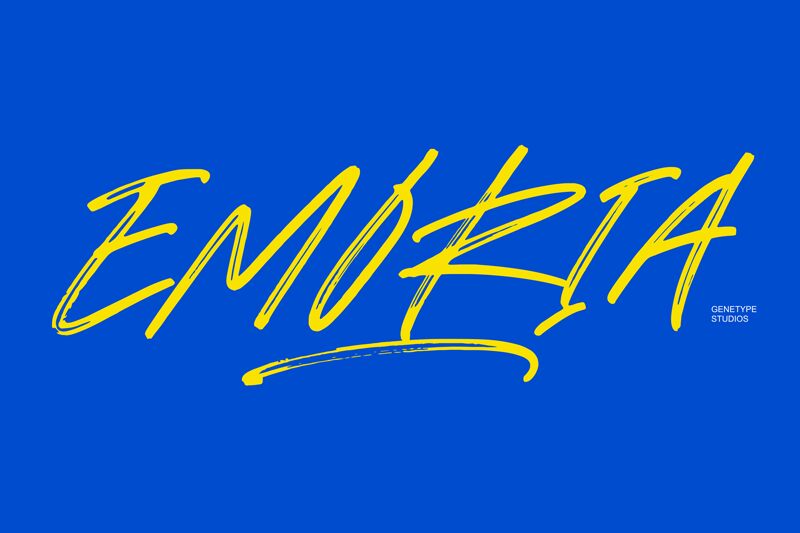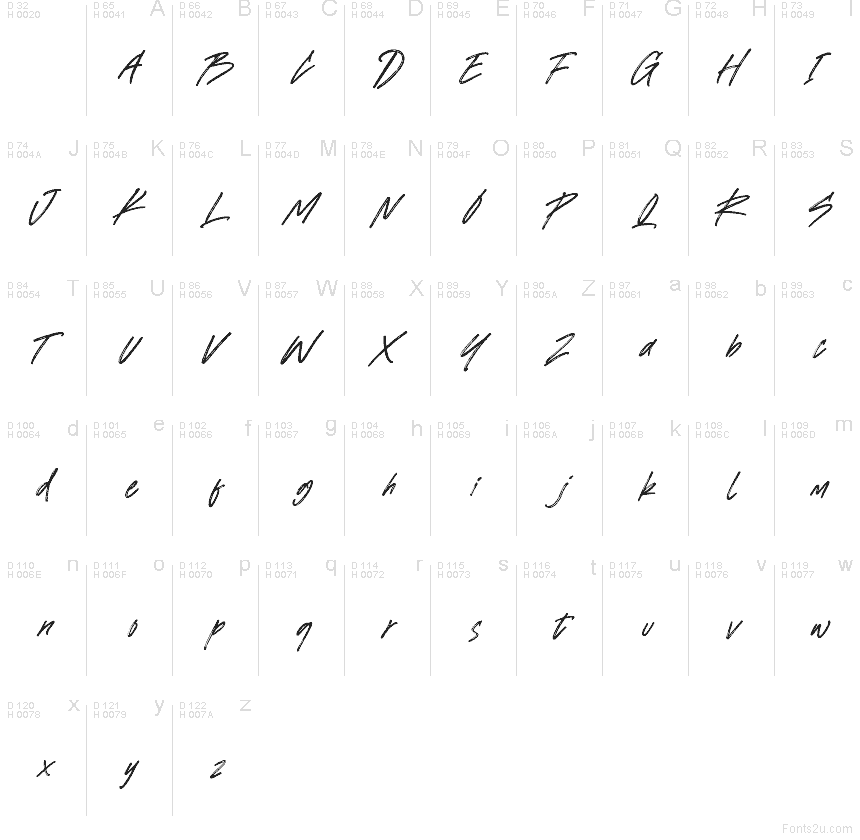
Emoria Brush od Genetypeco je bezplatné štětcové písmo v podpisovém stylu s rychlými, ostře se měnícími tahy a nezaměnitelně ručně psaným vzhledem. Dlouhé počáteční tahy a plynulá spojení dodávají písmenům dopředný pohyb, přičemž tenké linie ustupují tmavším stopám štětce a občasným okrajům suchého štětce. Tvary jsou volné a úhlové namísto pečlivě zaoblených nebo uhlazených.
Módní značky a hudební plakáty čerpají z jeho živého, osobitého výrazu. Hodí se také na obaly kosmetických produktů a pozvánky na akce, kde písmo může interagovat s inkoustovými skvrnami, plynulou linkovou kresbou nebo ručně kreslenými portréty jako součást obrazu namísto neutrální etikety.